Die Quadratnotation ist ein großer Schritt: Erstmals lässt sich die Tonhöhe einigermaßen verlässlich aufschreiben. Doch sie bleibt ein Hybrid aus Schrift und Erinnerung. Tonlängen, Rhythmus und Taktart sind nicht darstellbar — der lebendige Vortrag bleibt mündlich. Die genaue Tonhöhe ist mit Vorsicht zu betrachten: Sie hängt vom Stimmumfang des Chors und der Tradition des jeweiligen Klosters ab.
Quadratnotation
Die Quadratnotation ist die typische Notenschrift des Mittelalters. Vier Linien im Abstand von drei Halbtönen, am Zeilenanfang ein Schlüssel für C oder F — und schon weiß der Sänger, wo er steht. Die Tonlänge ergibt sich aus dem Text, Rhythmus und Taktart bleiben dem geübten Ohr überlassen.
Mittelalter, Linie für Linie
Vom Liniensystem zum Tischgebet
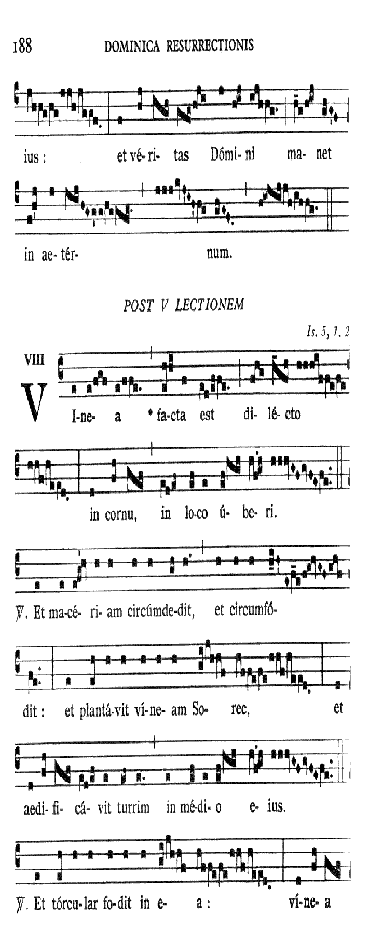
Aufbau
Vier Linien, ein Schlüssel
Quadratische Notenköpfe sitzen auf vier Linien. Der C- oder F-Schlüssel am Anfang weist dem Sänger seinen Halbtonschritt zu, der lateinische Text gibt Rhythmus und Tempo vor. Was wir heute als „starr“ empfinden, war im Mittelalter die feinste Präzision, die sich auf Pergament fixieren ließ.
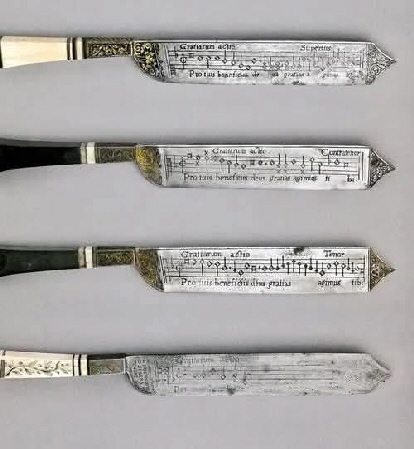
16. Jahrhundert
Gesungenes Tischgebet auf Stahl
Eine Kuriosität aus dem 16. Jahrhundert: Auf Messerklingen wurden gesungene Tischgebete eingraviert — Quadratnoten samt Text. Wer das Besteck zur Hand nahm, hatte das Lied auf der Klinge — Schriftkultur, geschmiedet in Eisen.